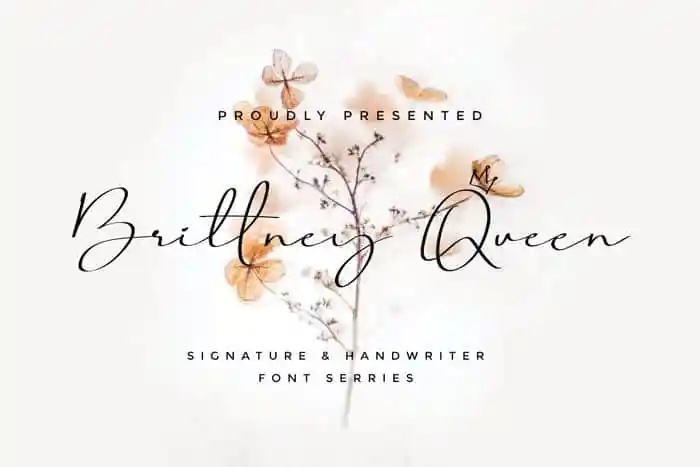
Brittney Queen Script Font – Download Grátis
Brittney Queen Script Font é uma fonte de script moderna que transmite beleza, elegância e contemporaneidade. Desenhada pelo designer Rantautype e disponibilizada através do site 99designs, esta fonte vem com ligaturas, swashes, alternativas estilizadas e conjuntos estilizados, oferecendo uma versatilidade impressionante para um vasto leque de projetos. Perfeitamente adaptada a criações como assinaturas, materiais de embalagem, logomarcas, recados, capas de livros ou revistas, cabeçalhos de site, roupas, marcas e embalagens, Brittney Queen Script Font é o elemento ideal para levar seu projeto ao próximo nível.